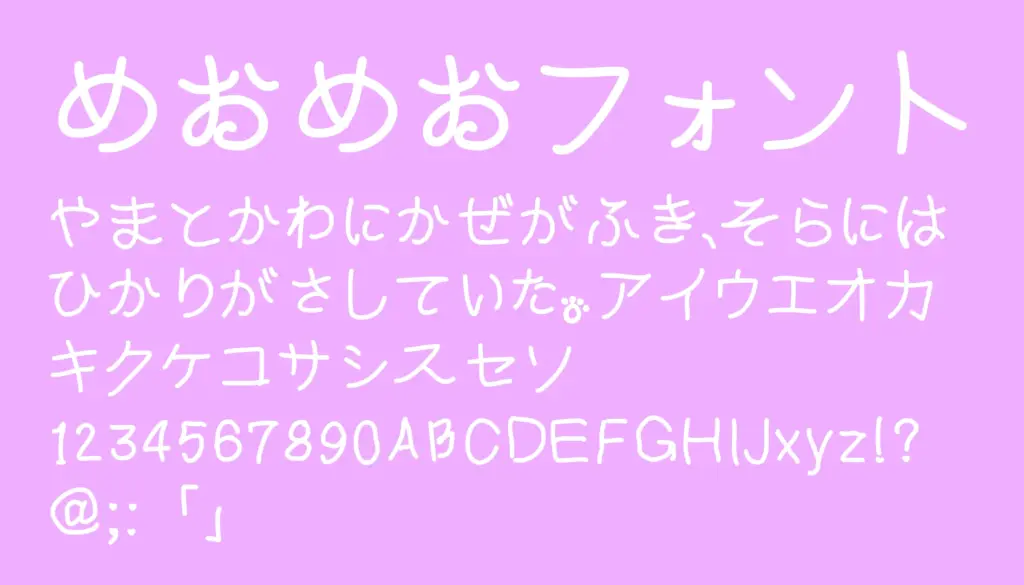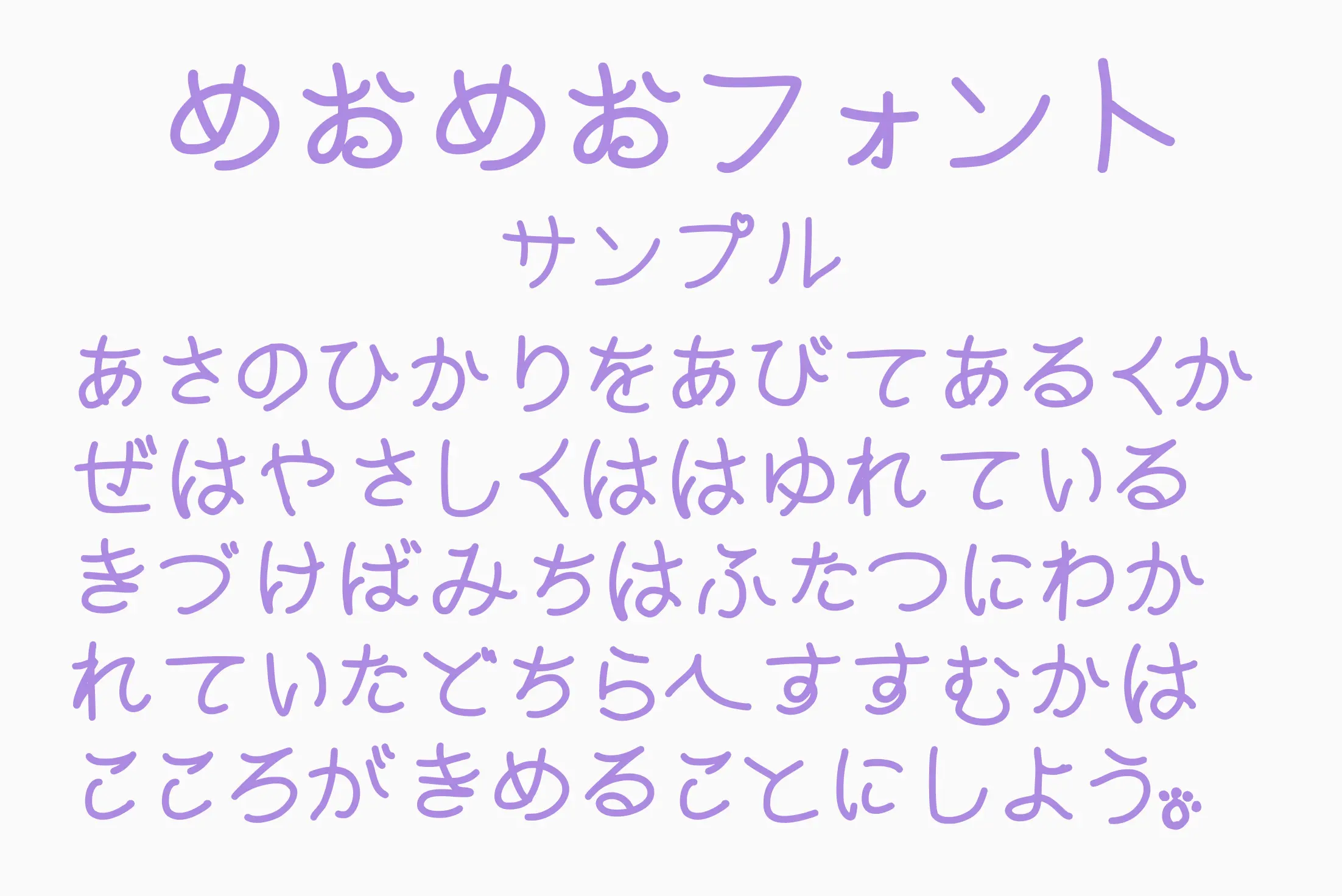
手書き風のやわらかさに小さなハートや遊び心を取り入れた、“ゆるかわ”系フォント。文字の中にさりげなく♥が入っているのが特徴で、かわいさ満点の個性派です。ひらがな・カタカナ・英数字に対応しており、女の子向けグッズ・イラスト・ポップ・SNS投稿などにぴったり。全体的にスリムで軽やかな印象なので、甘すぎず使いやすいのも魅力です。
めおめおフォント